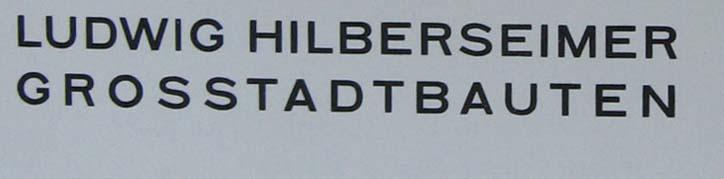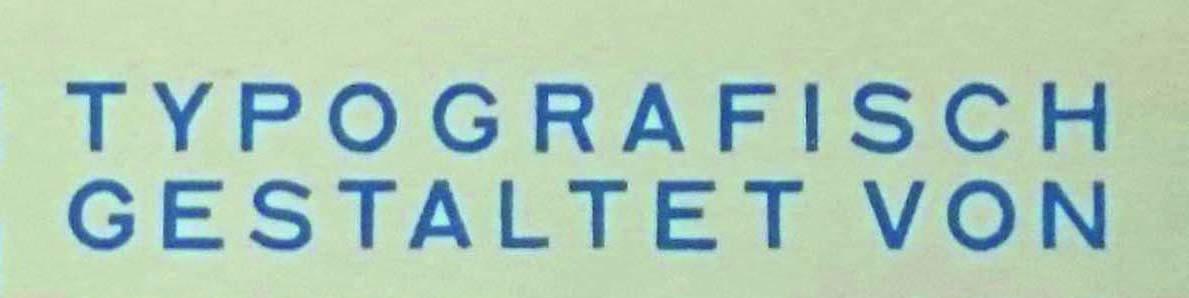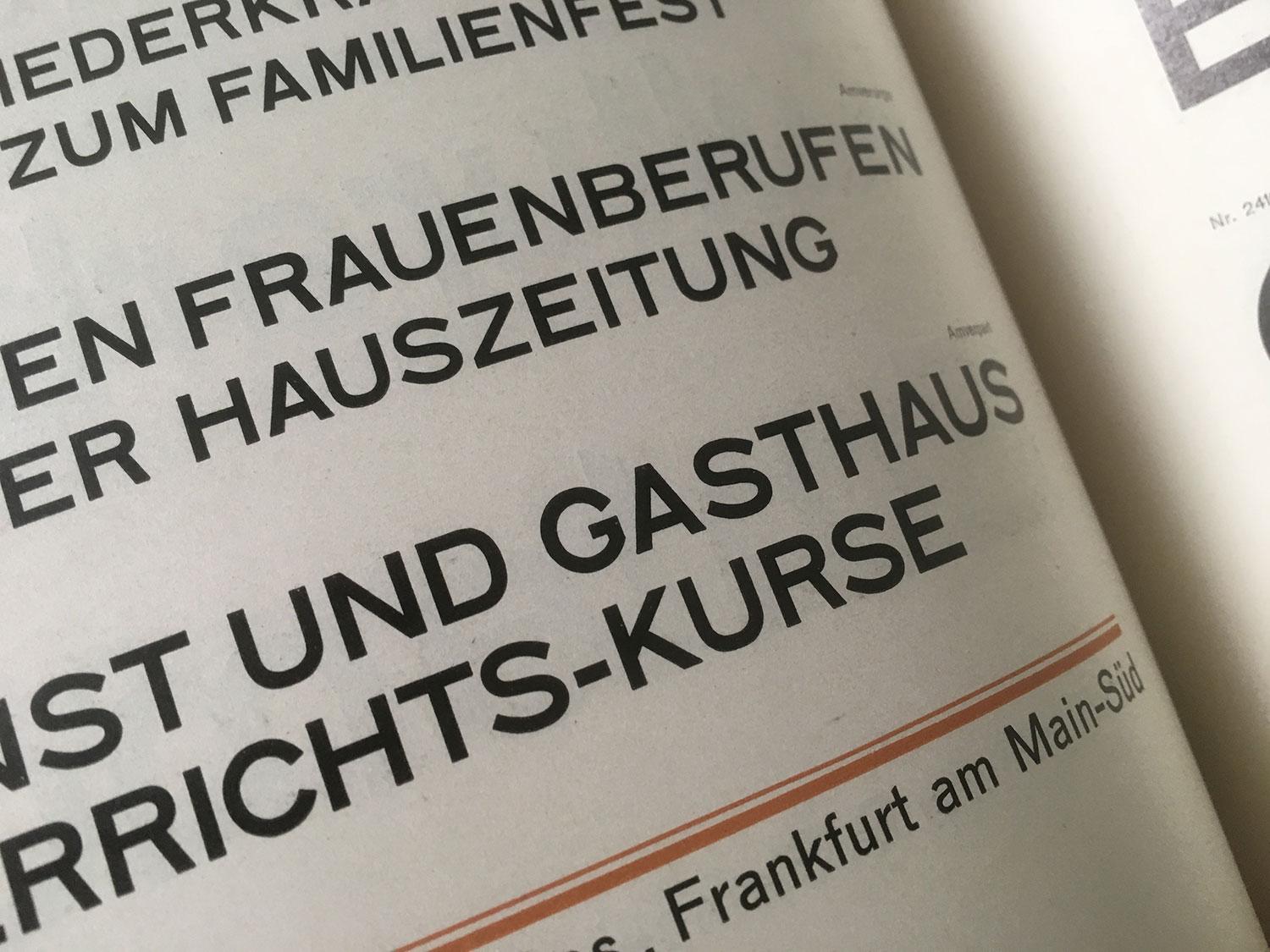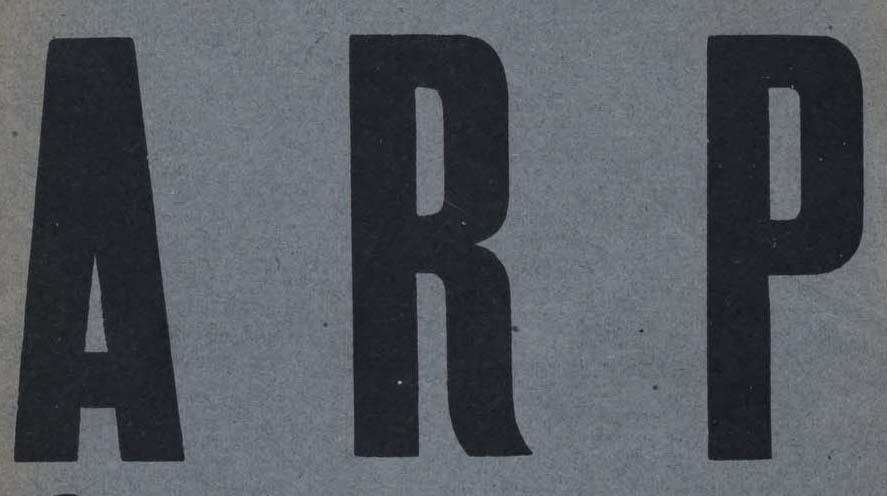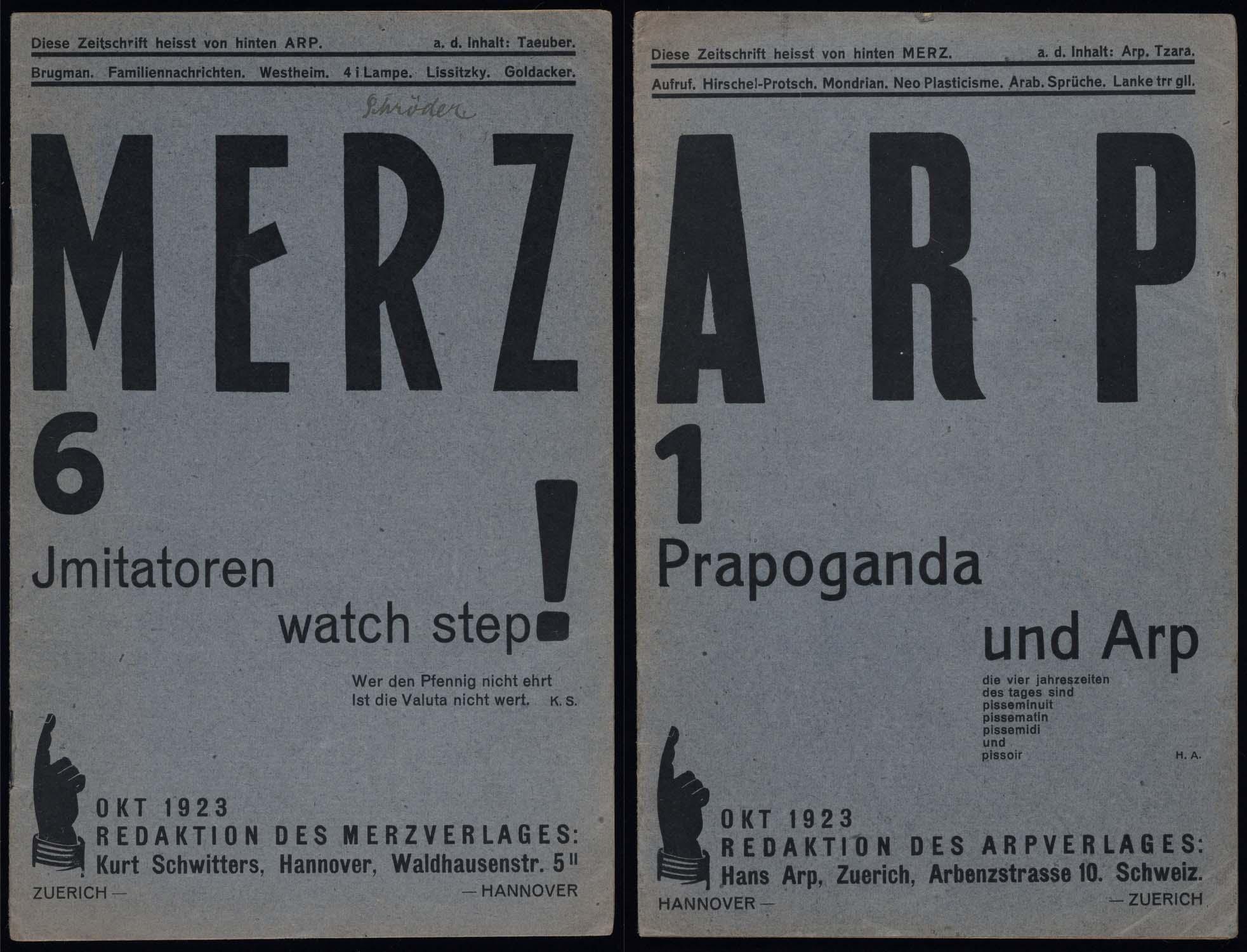
Suche Grotesk-Schrift (Kurt Schwitters)
im Rahmen meiner Masterarbeit über die werbegraphischen Arbeiten von Kurt Schwitters möchte ich gerne möglichst viele Schriften bestimmen können. Leider kann ich eine Grotesk-Schrift nicht genau identifizieren, weil die Gestaltung des Buchstaben "G" von allen gefundenen Schriften wie Koralle, Reform-Grotesk, Standard-Grotesk nicht übereinstimmt. Eventuell könnte es Grotesk-Bold oder Splendid sein, da fehlt mir aber die vollständige Buchstabenreihe.
Hat jemand eine Idee? Der Künstler verwendet die Schrift in dem Heft "Großstadtbauten" und "Die Scheuche"
Die Sackers Gothic geht in die Richtung:
Sweet Sans:
Engravers Gothic:
Irgendeine Schrift rumort mir noch im Kopf herum, die hat diese schmalen breiten Punzen … hach – ich komme gerade nicht drauf! @R:bert: R:::::::::::beeeeeert!
Hey, danke für eure Mithilfe. Die Engraver Gothic ist später entstanden, die blair scheint mit auch später zu sein.  Es muss eine Schrift sein, die in den 20ern in Deutschland gebräuchlich war. Vielleicht ist es wirklich die Reform in einem Schriftschnitt, der damals üblich war, jetzt aber nicht mehr zu finden ist. Wäre das eine Möglichkeit? Ich frage, wegen des "G"s?
Damals gab es ja noch keine Fonts, also digitalisierte Schriften. Es ist also gut möglich, dass entweder die Digitalisierung vom Original abweicht oder Deine Abbildung etwas zeigt, was noch gar nicht digitalisiert vorliegt. Da können Dir vermutlich nur Kollegen behilflich sein, die Schriftmuster dieser Zeit in ihren Archiven beherbergen. Also vielleicht @Microboy @RobertMichael oder @Ralf Herrmann.
für frühere Verhältnisse ist das »G« aus meinem Schriftmuster der Reform Grotesk 100% deckungsgleich zu dem unteren Bild von dir mit »Grosstadtbauten«
ich schau auf mein Schriftmuster – alles Reform Grotesk – und vergleiche die »R«s ... man scheints wohl nicht so ernst und dogmatisch genommen zu haben – wie auch die Schnitte der Akzidenz, bei der auch jeder seine Eigenheit hat. Und über die Zeit sind die Buchstaben sicherlich etwas modifiziert worden
Du meinst, die haben bei den Buchstaben manchmal geschlampt????  Was meinstt du mit "für frühere Verhältnisse" ist das Schriftmuster deckungsgleich?
früher = 20er Jahre ... die Schriftmuster kann man nicht so 100% passgenau abgleichen
geschlampt würde ich es auch nicht nennen aber die Schriftsätze mussten immer wieder neu produziert werden weil Bleibuchstaben nicht ewig haltbar sind d.h eine »Reform Grotesk« kann durchaus über die Zeit leicht anders ausgesehen haben. Dazu hatten die Schriften teilweise auch bei unterschiedlichen Größen unterschiedliche Buchstabenformen, weil eben auch auf die Größe angepasst wurde usw.
Nein, aber jeder Schriftgrad war ein eigener Entwurf und Abweichungen somit gang und gäbe. Und zwischen den Entwürfen der einzelnen Garnituren lagen gegebenenfalls Jahre und auch da gab es große Abweichungen. Im Extremfall wurden sogar unterschiedliche Schnitte verschiedener (übernommener) Schriftgießereien zu einer neuen Schriftfamilie zusammengestellt.
So oder so, ich hab mal in der großen Stempel-Probe geschaut und stimme zu: Das G und alle anderen Zeichen passen perfekt zur Reform-Grotesk.
Cool. Vielen Dank. Ihr habt mir sehr geholfen...Den "Schinken" würde ich auch gerne haben!!!!
Hallo alle, ich habe noch eine Schrift entdeckt, die ich nicht entziffern kann. Wer kennt diese Schrift?
Die üblichen Gegenfragen: Woher stammt das? Wann wurde es erstellt? Gibt es mehr Buchstaben davon?
Ich würde vermuten, da steht ARP ;-)
Entschuldige, aber das mit dem Entziffern konnte ich mir einfach nicht verkneifen.
Aber es ist eben allein an den Großbuchstaben  schwer zu ermitteln, was für eine Schrift dahinter steckt, wenn man für so eine alte Schrift nur z.B. den Seemann zur Verfügung hat, bei dem das gezeigte Schriftmuster aus den Wort Hamburgefons besteht, also nur das H als Großbuchstabe. Und von den darin gezeigten alten Schriften ist vermutlich nicht einmal ein Viertzel auch digital verfügbar.
Handelt es sich also, wie ich vermute, um eine Schrift aus der Zeit vor der Digital-Ära, ist es also angand von A, R und P kaum möglich, hier eine Aussage zu machen.
Die Schrift ist auf dem rückwärtigen Titel von Kurt Schwitters MERZ 6. Es ist eine Doppelnummer. Vorne steht MERZ hinten ARP. Die Wortmarke MERZ scheint aus selbstgestalteten Buchstaben zu bestehen. Aber ARP ist meiner Meinung nach eine geschnittene Grotesk-Schrift.
"In der Größe werden es wohl tatsächlich Holzlettern gewesen sein ..."
Was meinst du damit? Hat der Künstler sie selber in Holz geschnitzt? Kann der MERZ-Schriftzug auch aus Holzlettern gemacht worden sein? War das damals üblich?